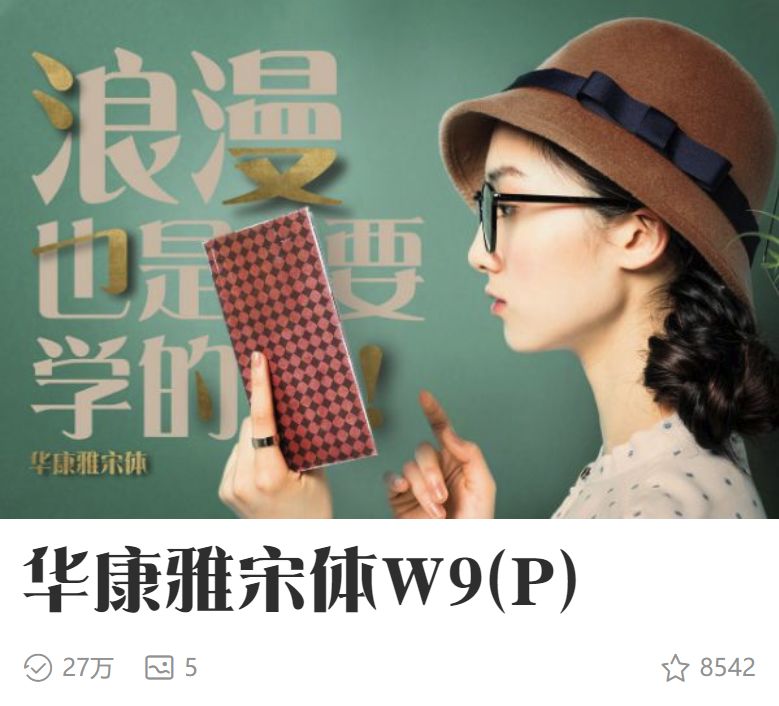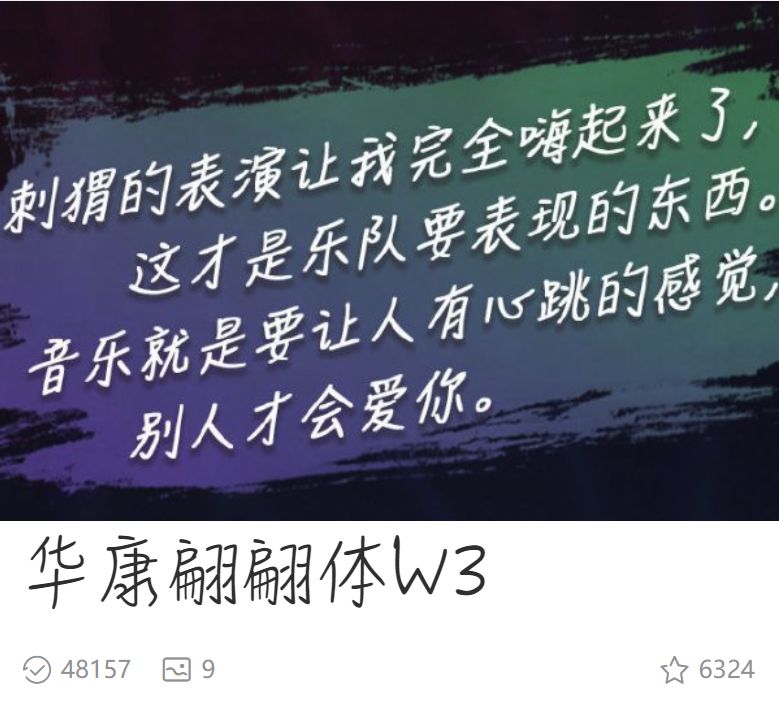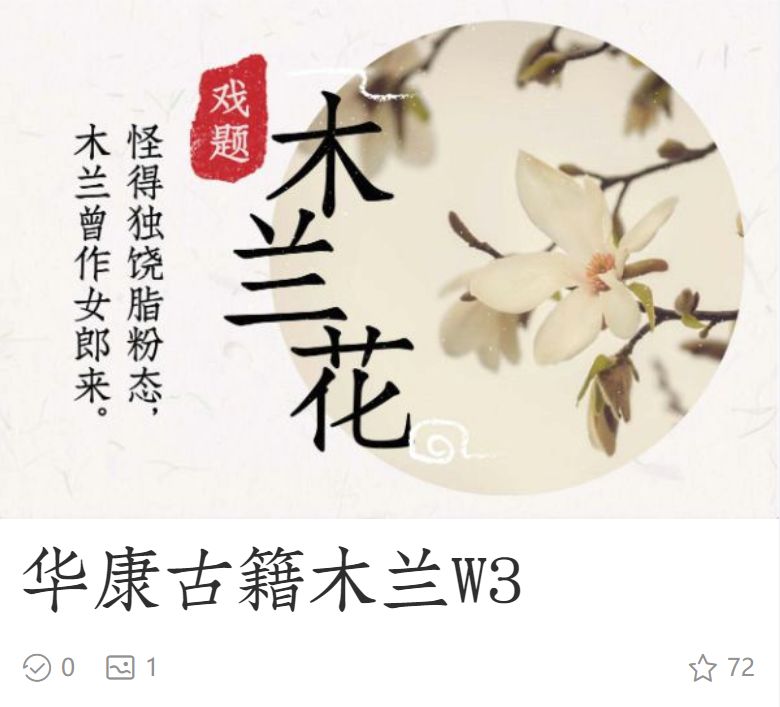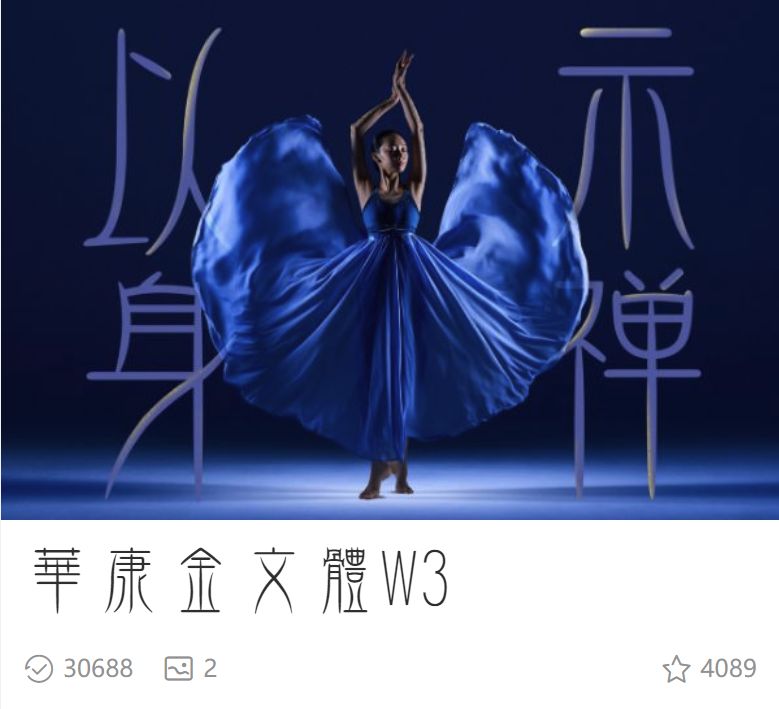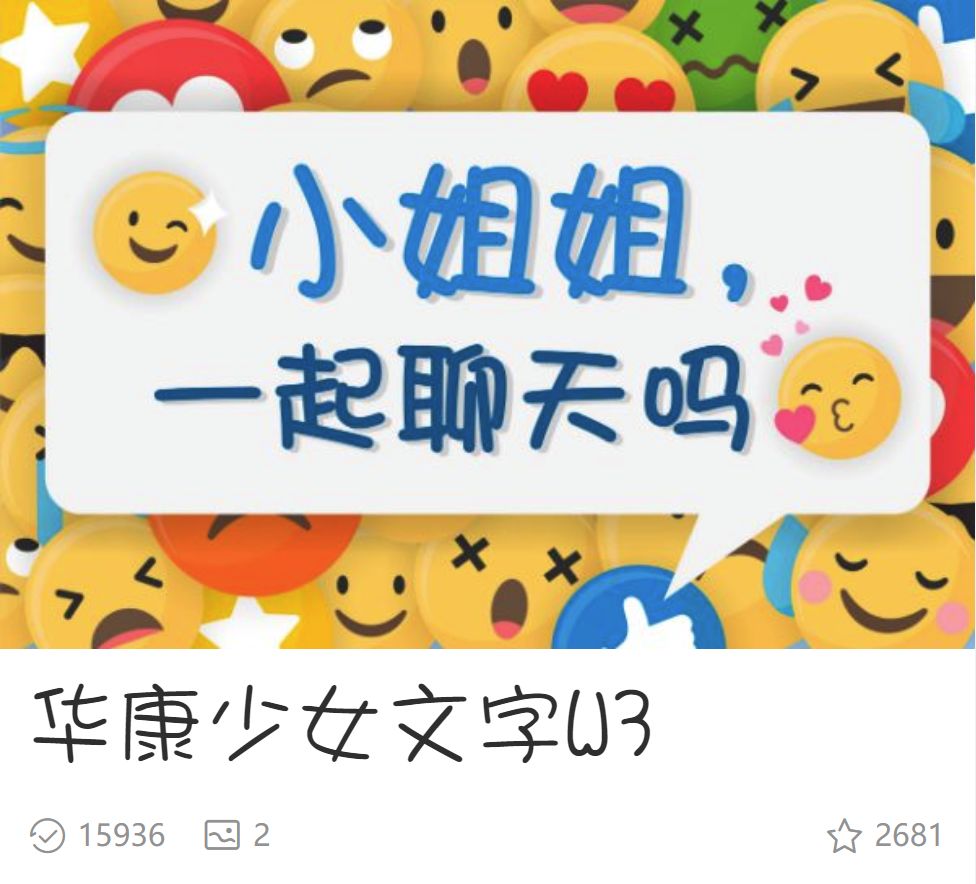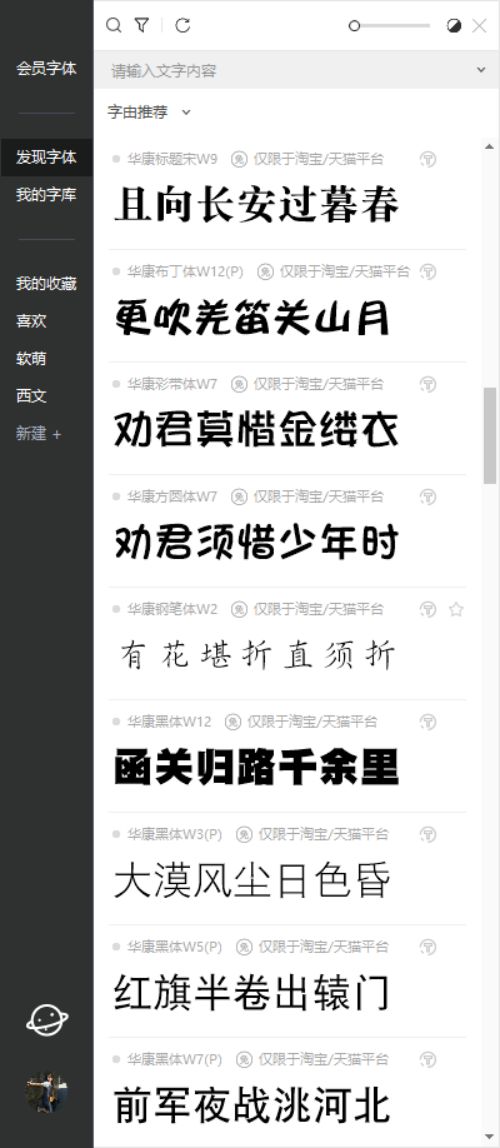
这个伴随80后成长的字体品牌,正式入驻字由啦!
如果我问你,刚接触计算机的时候,都用过哪些系统字,除了华文,就是华康吧!
1992年,中文Windows 3.1、Lotus 1-2-3皆采用华康细明体;后1994年微软Word中文版也以华康字体为其系统字;1996年Apple也选用了华康俪系列字体。至此,华康所出品的字体已广泛使用于计算机世界中。
它创立于台湾,后来还进军日本,并蝉联15年日本字体市占率No.1~
除了霸屏计算机,华康还陆续推出了古风字体~
以及下面这些爆款的个性化字体,有没有你熟悉的?